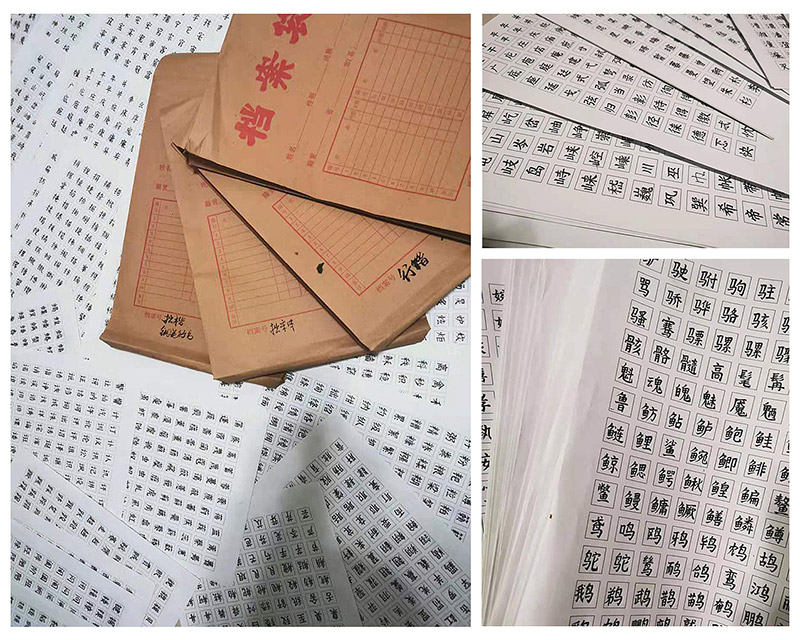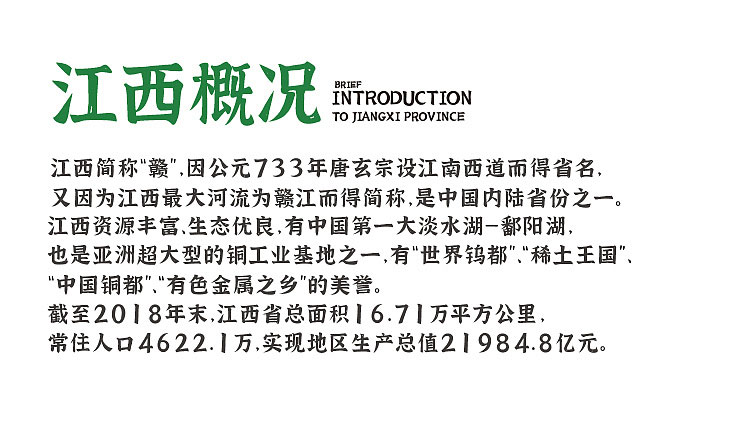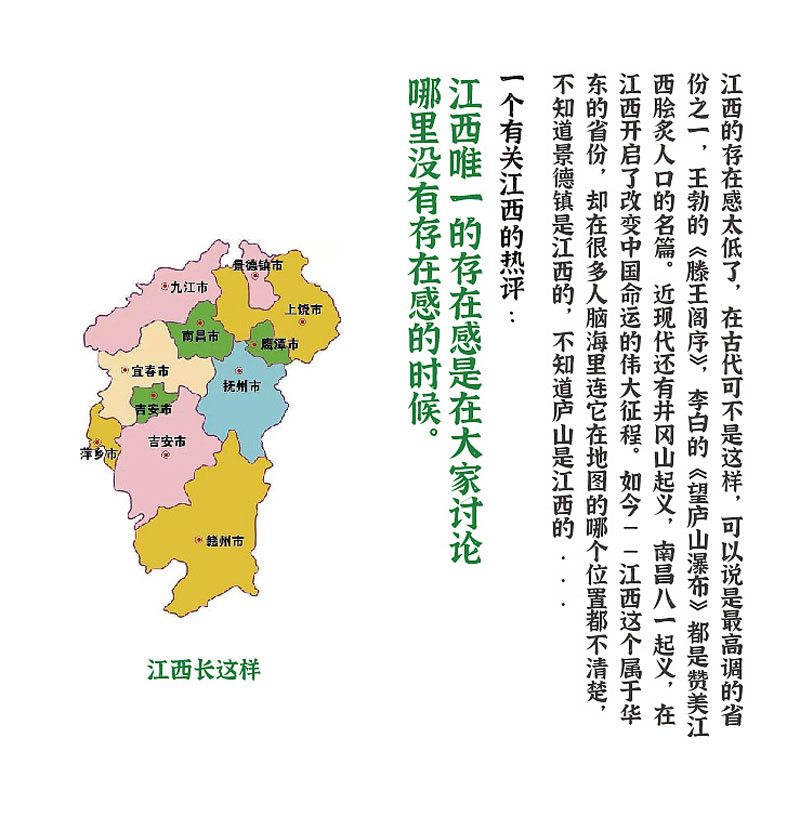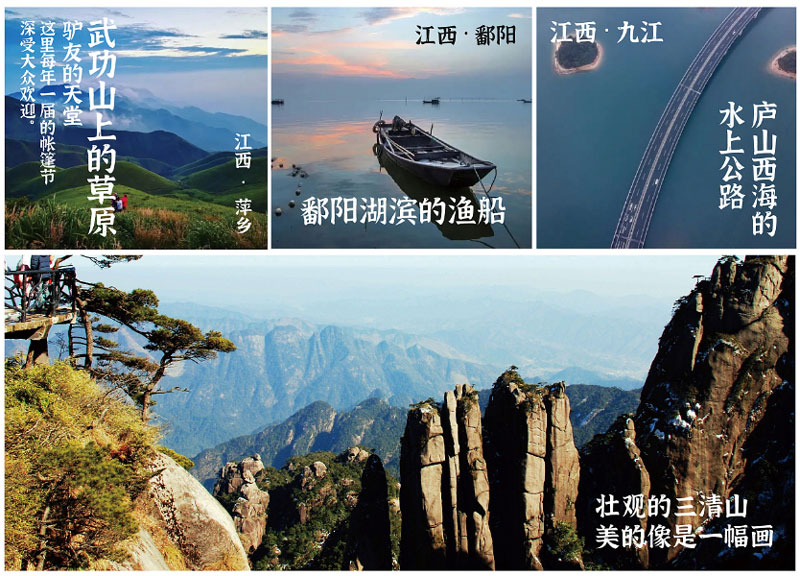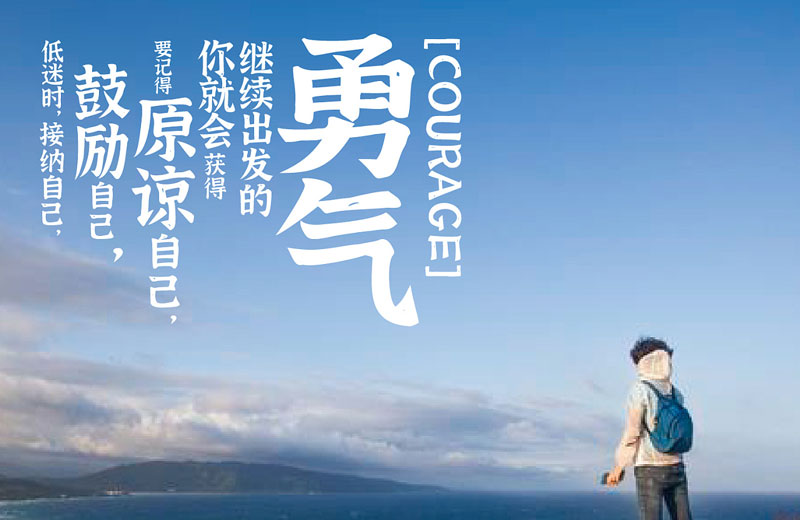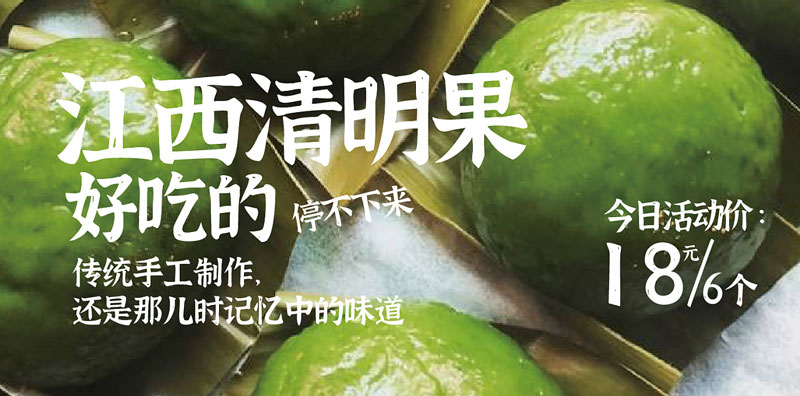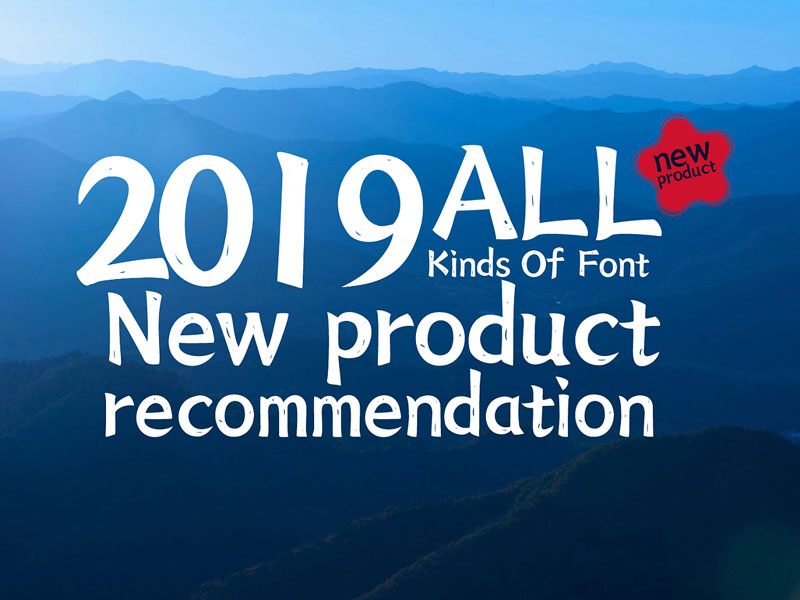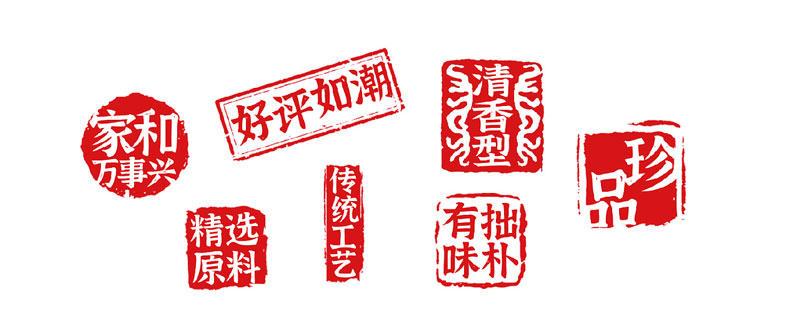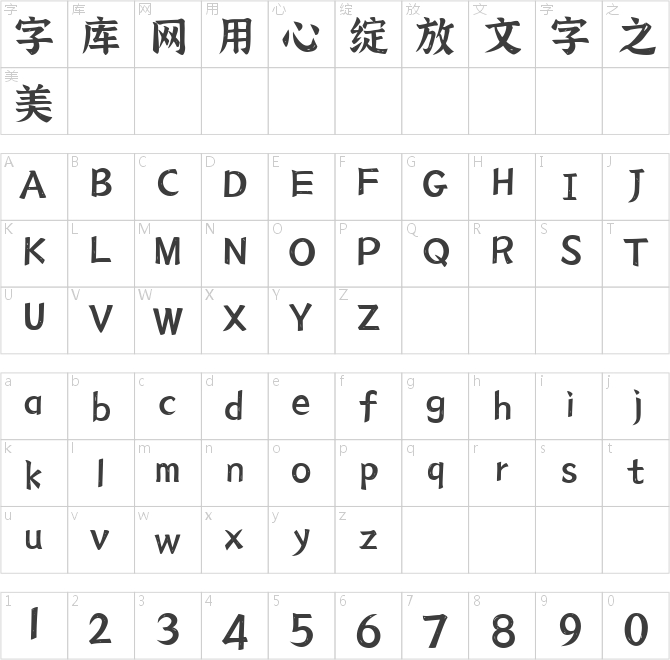
江西拙楷手寫楷體
「江西拙楷」是由字體設(shè)計(jì)師黃煜臣用半年時(shí)間獨(dú)立制作完成,對(duì)于這款字體的發(fā)布,黃煜臣不希望僅僅就是一款字體的展示,希望它能發(fā)揮更大的作用,帶來(lái)一些其他的價(jià)值,最終決定用這款字體為我們大江西做宣傳,并且用自己家鄉(xiāng)的名字命名
「江西拙楷」是一套手寫楷體,相比電腦中標(biāo)準(zhǔn)化制作的楷體,這套字體的筆畫會(huì)帶有一些書寫的痕跡,每個(gè)字的筆畫是沒(méi)有統(tǒng)一標(biāo)準(zhǔn)的,所以看上去顯得不夠規(guī)范,但是會(huì)有一種手寫的自然之感。
江西拙楷手寫楷體字體江西拙楷字庫(kù)是一款讓人賞心悅目、百看不厭的中文字體,適合各類廣告和產(chǎn)品包裝設(shè)計(jì)應(yīng)用,字體大小9.46MB,格式為ttf字體,上傳用戶是昊天金誠(chéng),作者/版權(quán)方為黃煜臣